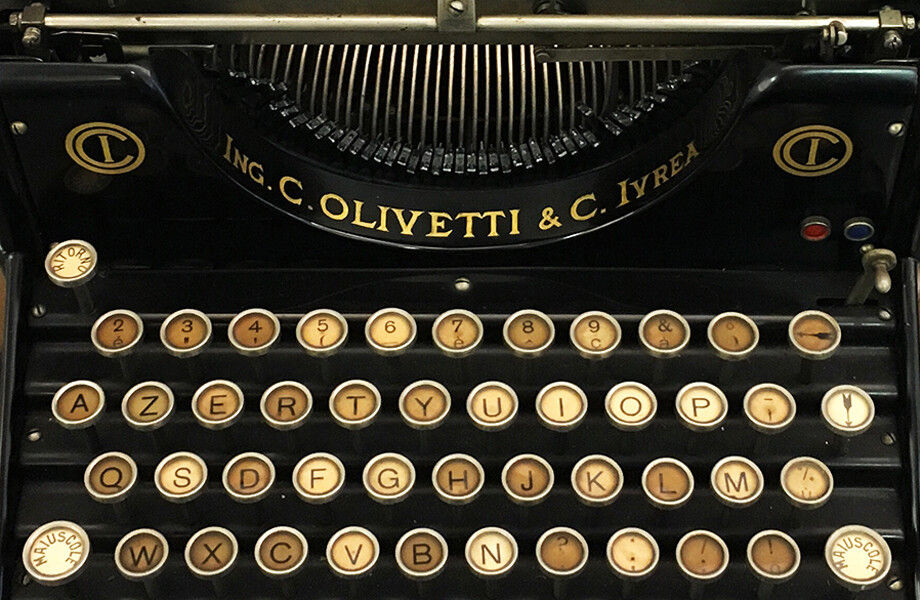
Cómo la máquina de escribir cambió nuestra forma de comunicarnos
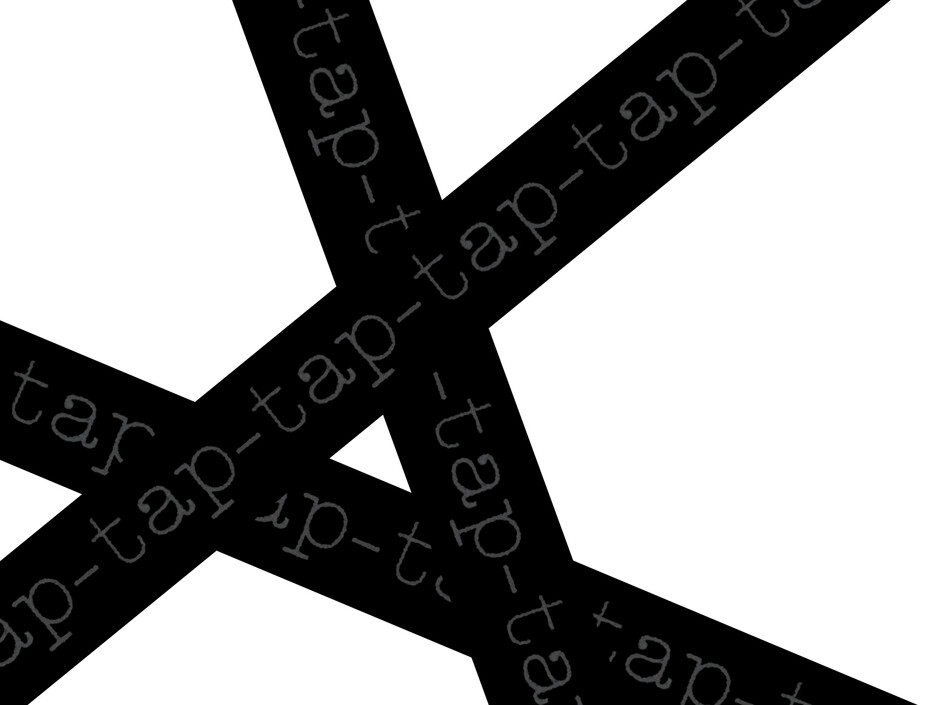
El sonido de la máquina de escribir mecánica nos resulta familiar a muchos de nosotros, que crecimos con su característico tintineo y repiqueteo. También es el sonido de una época pasada; una máquina que los ordenadores, las tabletas y los dispositivos móviles han dejado atrás.
La caída de la máquina de escribir es sólo un momento en una larga historia de cambios en la forma en que la humanidad ha utilizado la comunicación escrita, desde las pinturas rupestres a la talla de letras, y de la escritura a mano a los mensajes de texto. La humanidad simplemente no podría haber existido tal y como la conocemos sin la creación de marcas y la comunicación visual.
La evolución de la máquina de escribir
Las imprentas de Johannes Gutenberg a mediados de la década de 1450, que utilizaban la bella pero regimentada tipografía Blackletter, sentaron las bases de los conceptos iniciales de una máquina de tipos móviles para uso individual. En 1575, el impresor italiano Francesco Rampazzetto inventó el "scripture tattile", una máquina para imprimir letras sobre papel.
Más tarde, en 1714, el inglés Henry Mill registró una patente para "una máquina artificial o método para la impresión o transcripción de letras de forma individual o progresiva una tras otra". Así nació el concepto de máquina de escribir, y la continuación de la imprenta y la evolución de la tipografía pasaron a una nueva era.
Se cree que el primer aparato que utilizó el término "máquina de escribir" fue construido por el italiano Pellegrino Turri en 1808, diseñado para ayudar a los ciegos a comunicarse entre sí. El invento de Turri permitía imprimir papel carbón (utilizado como tinta) directamente sobre el papel mediante pequeñas teclas unidas a brazos metálicos provistos de caracteres en relieve. Cuando se pulsaba una tecla, el brazo golpeaba el papel carbón y hacía una letra impresa en el papel más grande. La novela de Carey Wallace de 2010 The Blind Contessa's New Machine se basa en la relación amorosa de Turri con la condesa Carolina Fantoni da Fivizzano.
En 1829, William Burt patentó la idea de los caracteres dispuestos alrededor de un marco giratorio y, durante los 40 años siguientes, numerosos inventores desarrollaron máquinas para crear el característico dispositivo de escritura tipográfica que conocemos hoy en día.
Fue Christopher Latham Sholes, impresor y editor estadounidense, quien patentó la primera máquina de escribir, ayudado por Carlos Glidden y Samuel W. Soule, de Milwaukee. Sholes concedió la licencia de su patente a Remington & Sons de Ilion, Nueva York; y en 1874 se comercializó el modelo 1 de Remington. Sholes también desarrolló el teclado e inventó el teclado QWERTY; a la Remington hay que agradecerle el pangrama "el zorro marrón rápido salta sobre el perro perezoso" como prueba para los potenciales mecanógrafos táctiles.
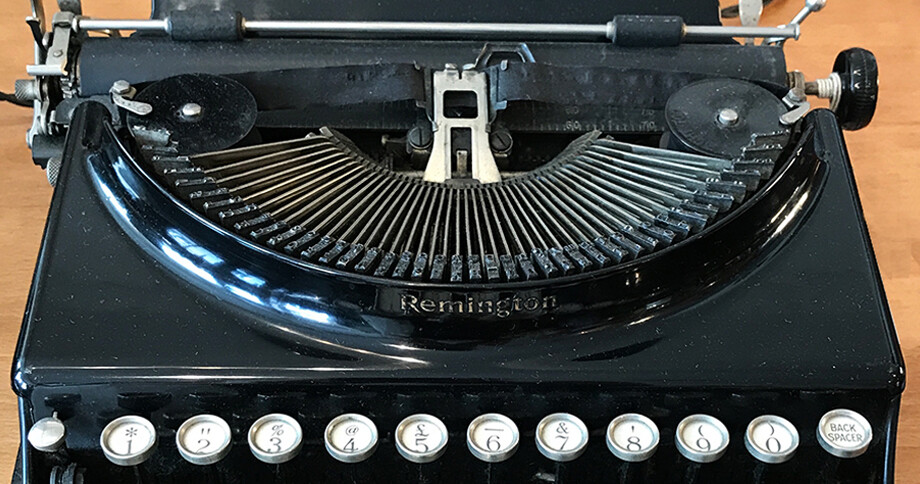
Trazado de tipos de máquina de escribir
Entonces, ¿de qué manera mejoró la máquina de escribir la tipografía y la comunicación? ¿Qué sabemos de las formas de las letras que imprimía la máquina de escribir? Con el tiempo se descubrió que las imprentas de letras negras de Gutenberg dificultaban la legibilidad, y el estilo gótico fue dejado de lado. Los nuevos avances tecnológicos de la imprenta entre 1500 y 1800, como el grabado, la litografía o la prensa rotativa, permitieron a los tipógrafos e impresores producir sublimes punzones de metal, que cambiaron para siempre las formas de las letras y los estilos de diseño. A medida que la máquina de escribir se hacía más y más popular, los fabricantes de máquinas de escribir diseñaban sus propias fuentes . Las distintas máquinas tipográficas producían resultados muy diversos, y los tipos de letra evolucionaban en forma y estilo.
Las primeras versiones de la máquina de escribir eran a menudo engorrosas y bastante laboriosas. También tenían limitaciones tipográficas en cuanto a las mayúsculas y la puntuación básica, debido a que el teclado consistía en una disposición alfabética de 36 teclas sin minúsculas ni números. Los números cero y uno se omitían, ya que en su lugar podían utilizarse la "i" y la "o" mayúsculas.
Originalmente, la disposición básica comprendía dos filas de 18 caracteres en la línea superior (3 5 7 9 N O P Q R S T U V W X Y Z) seguidas de la segunda fila de 18 (2 4 6 8 . A B C D E F G H I J K L M.).
La Remington Modelo 1 utilizaba un estilo Grotesco monoespaciado sin gracias. Esta forma de letra allanó el camino para un nuevo estilo tipográfico para la máquina en contraste con la densidad de la Blackletter, avanzando hacia un estilo limpio y sencillo fuente que permitía a la máquina de escribir un ancho fijo monolineal consistente. El modelo 2 de Remington, desarrollado en 1878, se convirtió en la primera máquina de escribir en tener una tecla Shift que permitía el uso de letras minúsculas, números y signos de puntuación extendidos como el signo de interrogación, el paréntesis, el ampersand y el símbolo de porcentaje.
El espaciado de las letras en las máquinas de escribir es rígido y se ajusta a una anchura restringida, de modo que cada carácter llena el espacio definido, creando lo que se conoce como monoespaciado fuentes. Se convirtieron en la norma porque las limitaciones de la máquina de escribir sólo permitían que la máquina avanzara a una medida determinada. Este tipo de configuración del texto altera la armonía, el equilibrio y la legibilidad; pero el monoespacio fuentes estableció un nuevo estilo de forma de letra.
Esclavo del ritmo
La máquina de escribir es sin duda uno de los inventos más increíbles e importantes de la historia de la humanidad. Tenemos mucho que agradecer a la "nueva máquina de escribir", como la describió Mark Twain. Cuando se concibió por primera vez, permitió una comunicación individual más rápida y sirvió para registrar documentos importantes sin necesidad de una imprenta. Lo mismo podría decirse de los ordenadores portátiles o los teléfonos móviles actuales, y si me detengo un momento a escuchar, todavía puedo oír un TAP - TAP - TAP, pero más suave, ligero y sutil.